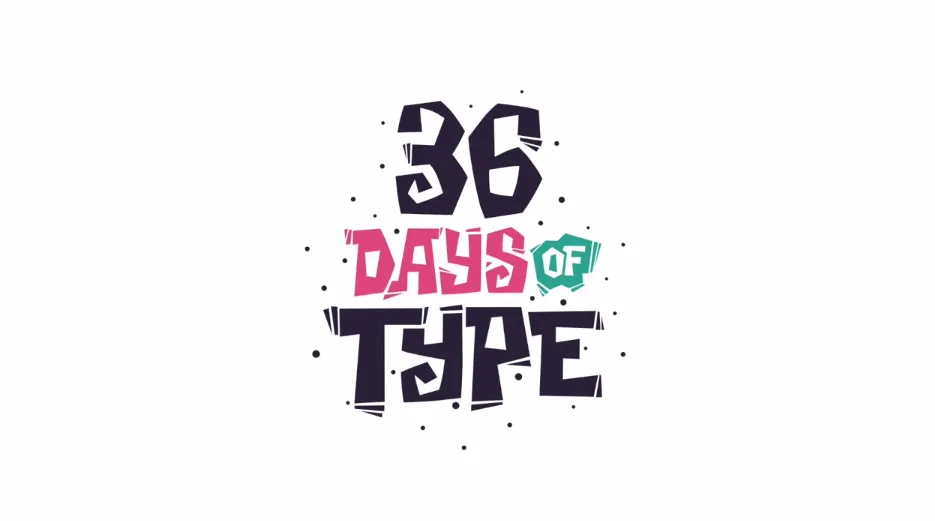
Projeto 36 dias de Tipografia
Nomeado como “36 Days of Type” o pessoal Shiffa convida designers, ilustradores e artistas para sua opinião particular para cada letra do alfabeto, cada letra com um estilo diferente.
O projeto foi desenvolvido em 36 dias daí o nome, em cada dia cada profissional mostrava um estilo de uma letra ou número sem que perca a sua forma tradicional, além de muito criativo este projeto é muito divertido, haja criatividade vale a pena ver.
“36 dias, 36 tipos, 36 ideias, 36 estilos diferentes. Eu sou Shiffa e este é meu 36 dias de tipografia”, diz o criador do projeto.